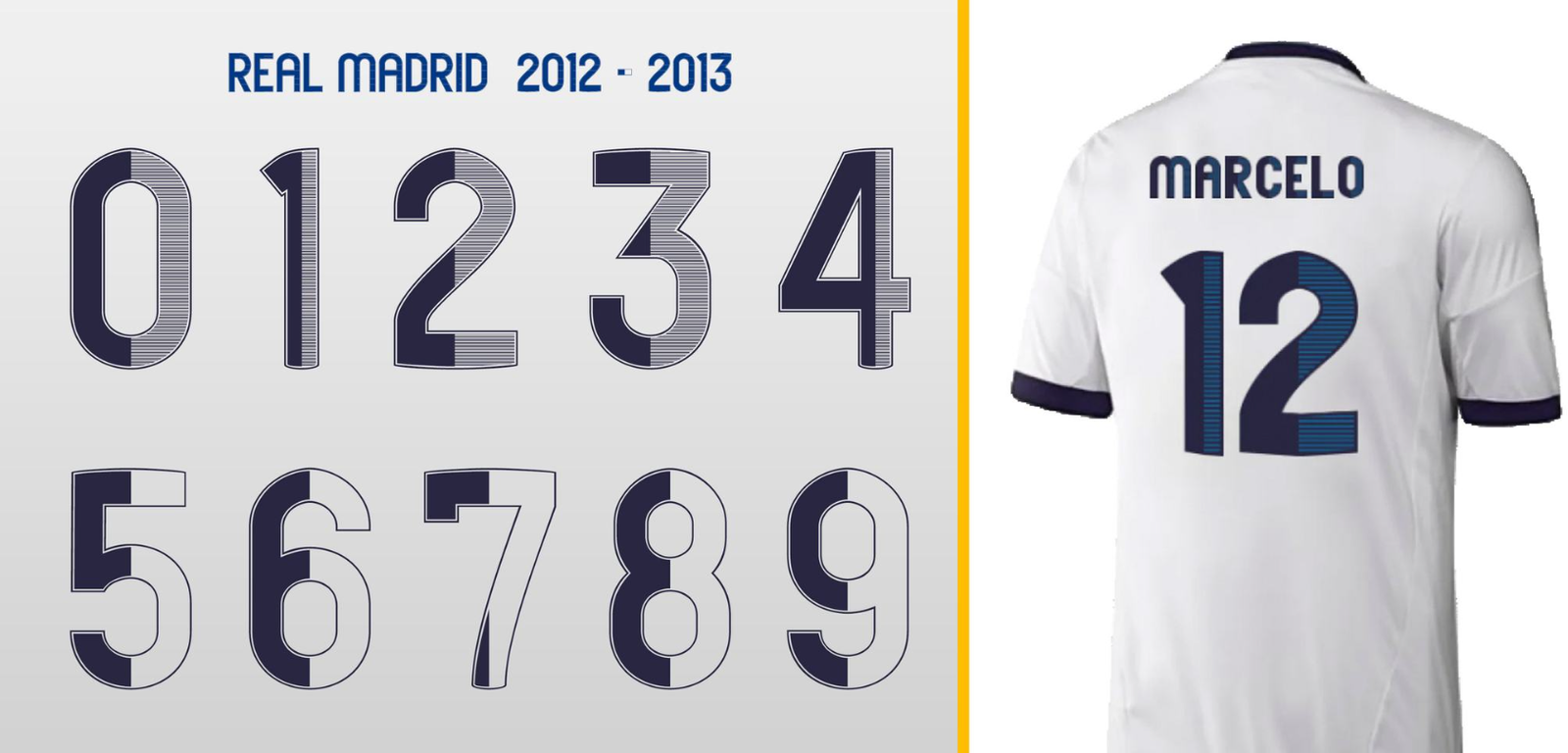
Relembre uma das épocas mais marcantes da era moderna dos “Galácticos”. A temporada 2012/2013 do Real Madrid não foi apenas especial pelo elenco estelar comandado por José Mourinho, mas também pelo design icônico apresentado pela Adidas em comemoração aos 110 anos do clube.
Se você busca a tipografia exata que estampou as costas de lendas como Cristiano Ronaldo (CR7), Mesut Özil, Kaká e Sergio Ramos, você está no lugar certo. Disponibilizamos o arquivo perfeito para restaurar camisas antigas ou criar novos projetos de design esportivo.
Estilo Visual e Aplicação
A fonte desenvolvida pela Adidas para esta temporada específica fugiu do padrão tradicional. Com um visual futurista e angulado, ela se destaca pelos cortes diagonais sutis e pelo aspecto “blocky” (blocado), que remete a uma estética industrial e imponente.
No uniforme titular (branco com detalhes em azul marinho e turquesa), a fonte cria um contraste elegante e moderno. É uma tipografia que transmite força e velocidade, características marcantes daquele time que jogava em contra-ataques letais. É ideal para quem deseja recriar a “Era de Ouro” de CR7 no Santiago Bernabéu.
Dica de Ouro: Para a personalização perfeita da camisa Home (Branca), utilize a fonte na cor azul marinho escuro. Para a camisa Away (Azul Marinho), a aplicação correta é na cor amarelo-neon/verde elétrico.